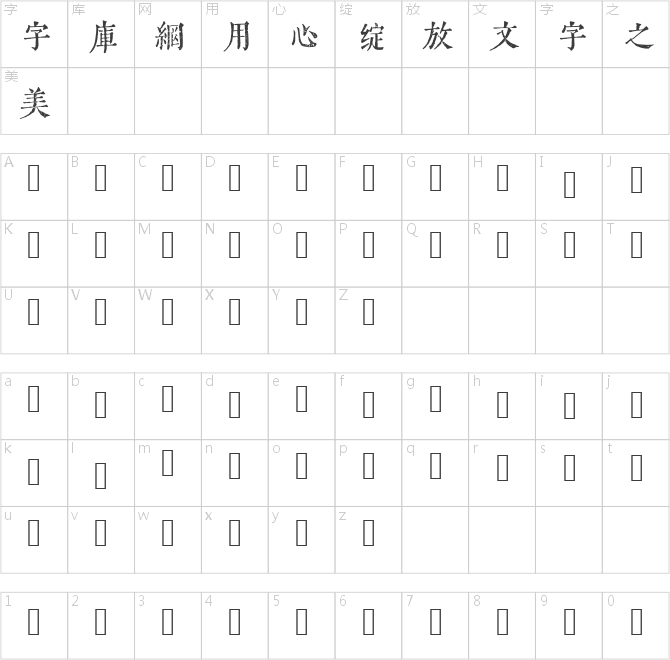
令東齊伋復(fù)刻體
黃令東
令東齊伋復(fù)刻體字體黃令東齊伋復(fù)刻體字庫(kù)是一款讓人賞心悅目、百看不厭的中文字體,適合各類廣告和產(chǎn)品包裝設(shè)計(jì)應(yīng)用,字體大小39.58MB,格式為ttf字體,上傳用戶是白刃寒走得慢,作者/版權(quán)方為黃令東